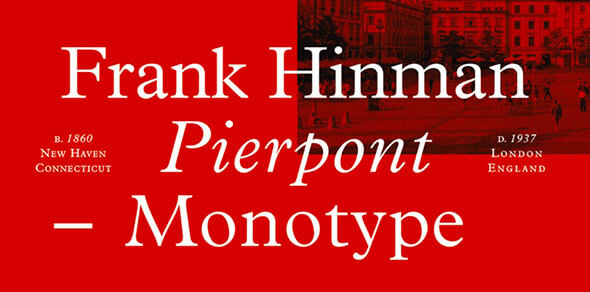
お気に入りを見つけよう!Webでも印刷でも使える、最新セリフフォント集!【Webセーフフォントも】
この記事では今すぐにでも試してみるべき、非常に美しいセリフフォントを25種類紹介します! New Yor TimesとNew York Journalで使われている人気のあるフォントから、新しいデザイナーが公開したばかりの、それほど有名ではないものの、同じぐらいきれいで美しい新鮮なセリフフォントまで、このリストはあなたのプロジェクトに適したセリフフォントを見つけるのに役立つことでしょう。
これらの最高のセリフフォントは、Webプロジェクトと印刷物の両方に使用でき、いくつかは無料でダウンロードすることもできます。下のリストには、スラブセリフフォント、大文字フォント、エレガントセリフフォント、モダンセリフフォント、伝統的セリフフォント、ヴィンテージフォントなどがあります。
以下のリストから、使ってみたいフォントを選んでみましょう。オンラインマガジン、ブログ、オンラインニュースのためのフォントが必要な人のために、Webセーフフォントも紹介しますよ!
Geogia
Geogiaは多分皆さんおなじみのセリフフォントでしょう。このフォントはボディテキストとして使用するのには完璧ですが、見出しやタイトル用のフォントとしても優れています。これはウェブセーフでシンプルでエレガントなセリフフォントです。読みやすいためブログにも最適です。
Cheltenham
Cheltenhamフォントファミリには、さまざまな重さとバリエーションが含まれています。、印刷物とウェブ媒体の両方で美しく、時代遅れではない伝統的な外観をしています。またとても読みやすいです。
Grad
Gradは、タイトル、見出し、メニューなどを強調するためにさりげなく使える美しいセリフフォントです。本文よりもむしろ見出しに使った方が映えます。
Plantin
Plantinはスタイリッシュでエレガントな見た目の、よく知られたフォントです。このセリフフォントは、Webプロジェクトと印刷プロジェクトの両方に適しています。読みやすく、シリアスで、プロフェッショナル、そしてクラシックな印象を与えます。
Sentinel
Sentinelは見出しと本文の両方に使用できる汎用セリフフォントです。読みやすく、どんなタイプのデザインに使っても素敵です。
Adobe Caslon Pro
Adobe Caslon Proは、読みやすく、新聞や雑誌などの印刷プロジェクトに使うのが理想的で、視覚的に大変魅力的なセリフフォントです。読者にプロフェッショナルな雰囲気を感じさせたい場時には、このフォントを使用しましょう。
Guardian
Guardianは、沢山のテキストを含むプロジェクトで使用できる素晴らしいセリフフォントで、新聞や雑誌に適しています。読みやすく、ウェブサイトにも使用できます。
Eames Century Modern
Eames Century Modernは、読者の目を引く一風変わったセリフフォントです。見出しに使って、デザインにスタイルと大胆さを与えましょう。
Stanley
Stanley セリフフォントはNew York Timesのクリエイターからインスピレーションを受けてデザインされています。それは現代的なルックスの角張ったセリフ字体です。大きなポスターに向いていて、新聞記事の見出しにも適しています。
Freight Text Pro
Freight Text Proは、さまざまな太さが用意された多目的セリフフォントです。見出しから本文に至るまであらゆる場面で簡単に使用でき、誰にとっても読みやすいような流れをコンテンツに与えてくれます。
Exchange
Exchangeは読みやすいセリフフォントです。Wall Street Journalで見かける、広く用いられていて良く目立つフォントです。ウェブサイトに使っても効果的です。
PT Serif
PT Serifは、小見出しや本文に使用できる、大変実用的なフォントで、心地よく読むことができ、大変美しいです。
Harriet
Harrietは現代的な雰囲気を持つエレガントで伝統的なセリフフォントです。 現代的なデザインと伝統的なデザインを完璧な融合を成し遂げていて、見出しにも本文にも使用できます。
Butler
Butler by Fabian De Smetは、BodaniフォントとDala Flodaフォントからインスピレーションを受けている、豪華で現代的なセリフフォントです。 書籍やその他の印刷物、見出し、招待状などに向いています。
Fakedes
FakedesはCyril Mikhailovによってデザインされた素晴らしいセリフフォントです。 このフォントは二重線で構成された丸っこいセリフフォントであるため、見出しや印刷物でのみ使用できます。
Muchacho
Muchachoは、大文字の楽しい雰囲気のセリフフォントです。 この素晴らしいフォントはJeff Schreiberによってデザインされたもので、見出し、印刷、Webサイト、ロゴなどに使用できます。
Poly
PolyフォントはNicolásSilvaがデザインしました。 垂直を強調し、フォント全体を通して伝統的でエレガントなデザインを持つWeb用セリフフォントです。
Barbaro
BarbaroはIvánNúñezによってデザインされた、素晴らしいもう一つのフォントです。 このセリフフォントにはヴィンテージ感があり、60年代の雰囲気を持つプロジェクトに最適です。
Firefly
Fireflyはヴィンテージ風のセリフフォントです。 この素晴らしいフォントはSean Coadyによってデザインされたもので、自由にダウンロードして使用できます。
Pelmeshka
Pelmeshkaは、Bodoniフォントにインスパイアされて生まれたもう一つのセリフフォントです。 子供らしい雰囲気を持つこの楽しげなフォントは題名、見出し、印刷物に最適です。 Cyril Mikhailovがデザインしました。
Fénix
Fénixは、Fernando DíazとTipoType Foundryがデザインしたセリフフォントです。 読みやすいこのフォントは大きいひげ飾りと荒々しい筆跡が特徴です。 優雅で現代的で、見出しにも本文にも適しています。
Molesk
Moleskは、Pedro Loboによってデザインされたセリフフォントで、大文字のみです。 このスラブセリフフォントは古い他のフォントを模倣していて、文字の右横には興味深くて、繊細に表現された影があります。
Rancho
Rancho には3種類のスタイルとWild Westデザインが付属しています。 それはNach Ohによるデザインです。
Bariol Serif
Bariol serifフォントはAtipoがデザインしました。 このフォントの線には無駄が無く、読みやすいです。 見出しと本文の両方に使用できます。
Yeseva One
これは伝統的な見た目のセリフフォントです。 フォントの細部は優雅で、少しだけ女性的な印象を与えます。 TypeTypeによるデザインです。。